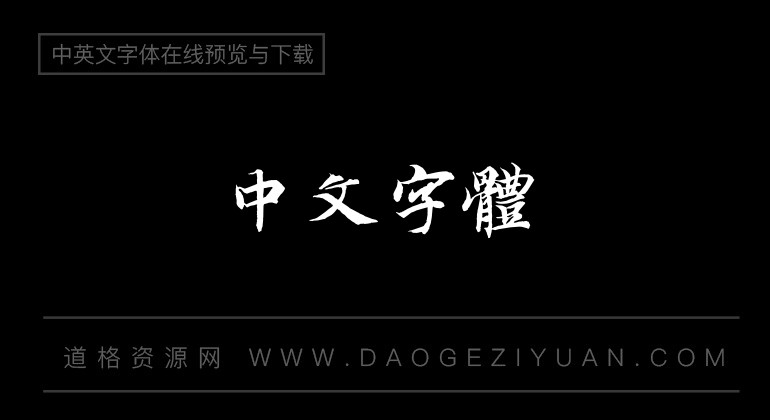
迷你繁智楷是一款由清华紫光设计团队研发的字体,它是一款结合了中国传统文化和现代技术的繁体字字体。这款字体以繁体楷体为基础,结合了清华大学紫光科技研究院的技术,采用了现代技术来完善传统楷体字的细节,使得每一个字看起来更加精美,更具有现代感。这款字体拥有清晰的线条,细腻的结构,以及精致的笔画,可以更好地表达文字的内涵和美感。文件名:MiNiFanZhiKai-1.ttf
迷你繁智楷是一款非常不错的手写艺术字体,具有很好的视觉感,适合于文化类的宣传设计、商业类品牌的广告和产品包装设计以及个性化文字排版等较多场景。